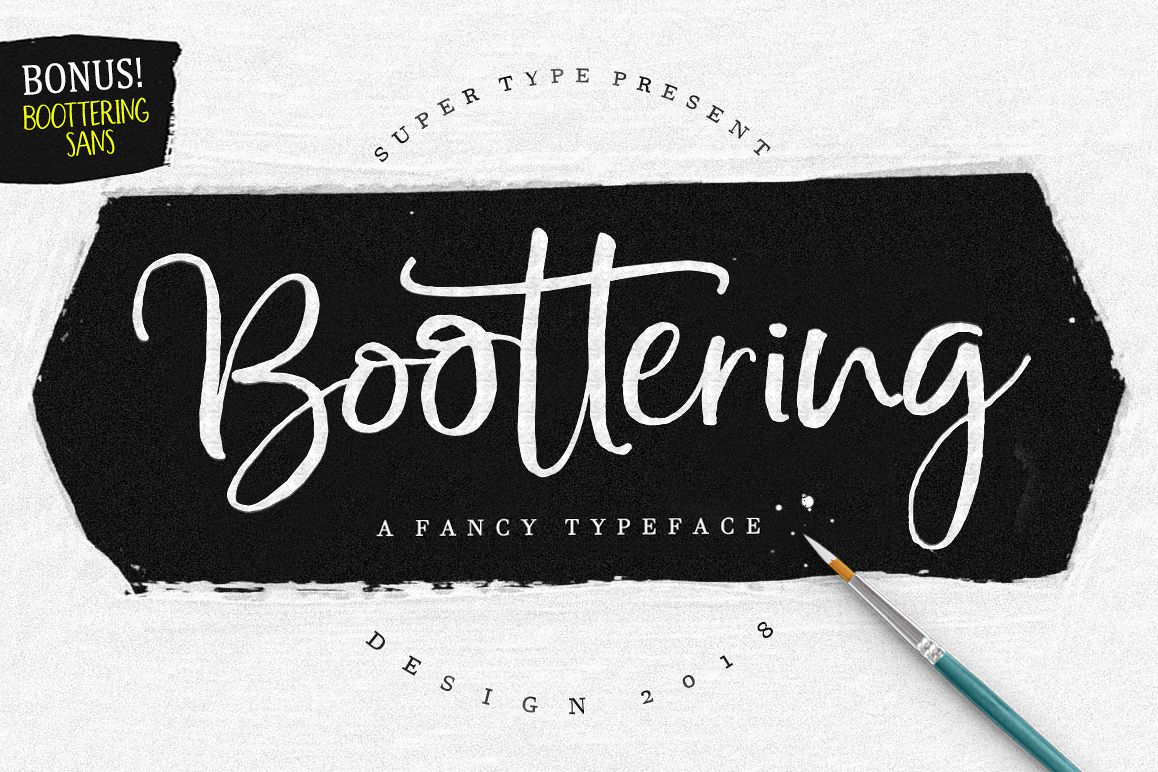
Boottering | Font Duo
Boottering adalah skrip buatan tangan modern, organik, energik dan dinamis, dapat digunakan untuk berbagai tujuan. seperti judul, korespondensi, undangan pernikahan, kop surat, papan nama, label, buletin tanda tangan, logo, poster, lencana, dll. Fitur booting 222 Glyphs, 40 alternatif semua karakter huruf kecil, termasuk ligatur, Dukungan internasional untuk sebagian besar Bahasa Barat adalah termasuk, Dan untuk Boottering Sans tidak memiliki dukungan Bahasa Internasional. File termasuk: -Boottering (otf, ttf) -Boottering Sans (otf, ttf) Untuk mengaktifkan OpenType Stylistic alternates, Anda memerlukan program yang mendukung fitur OpenType seperti Adobe Illustrator CS, Adobe Indesign & CorelDraw X6-X7, Microsoft Word 2010 atau versi yang lebih baru. Boottering dikodekan dengan PUA Unicode, yang memungkinkan akses penuh ke semua karakter tambahan tanpa memiliki perangkat lunak perancangan khusus. Pengguna Mac dapat menggunakan Font Book, dan pengguna Windows untuk menempelkan ke aplikasi / editor teks favorit Anda. Cara mengakses semua karakter alternatif, menggunakan Windows Character Map dengan Photoshop: https://www.youtube.com/watch?v=Go9vacoYmBw https://www.youtube.com/watch?v=XzwjMkbB-wQ